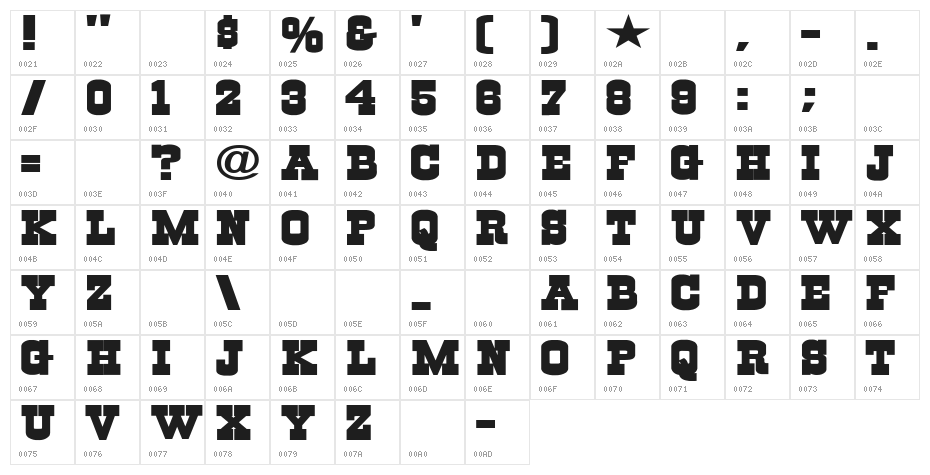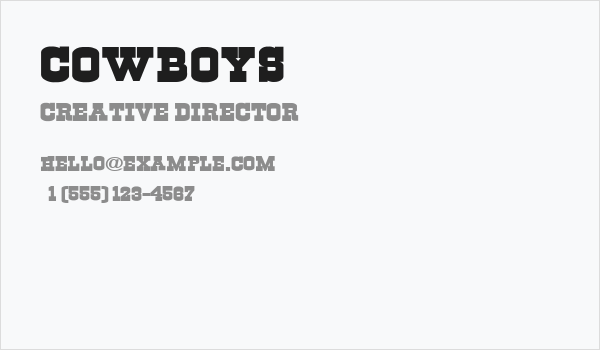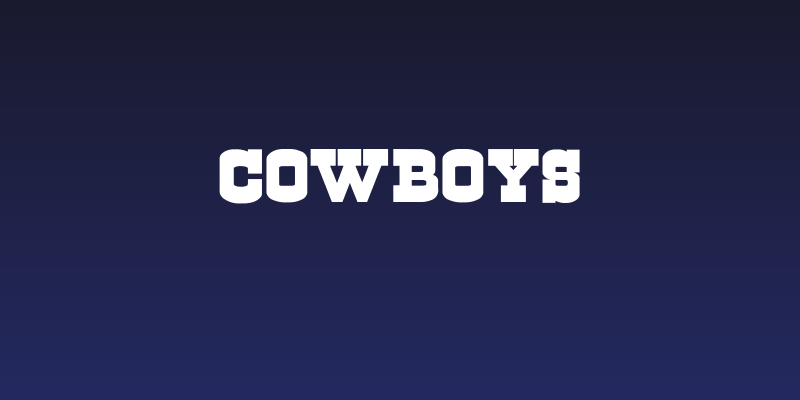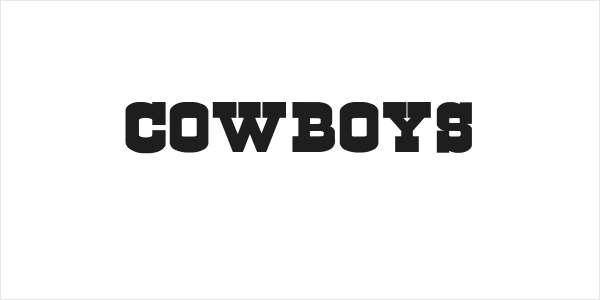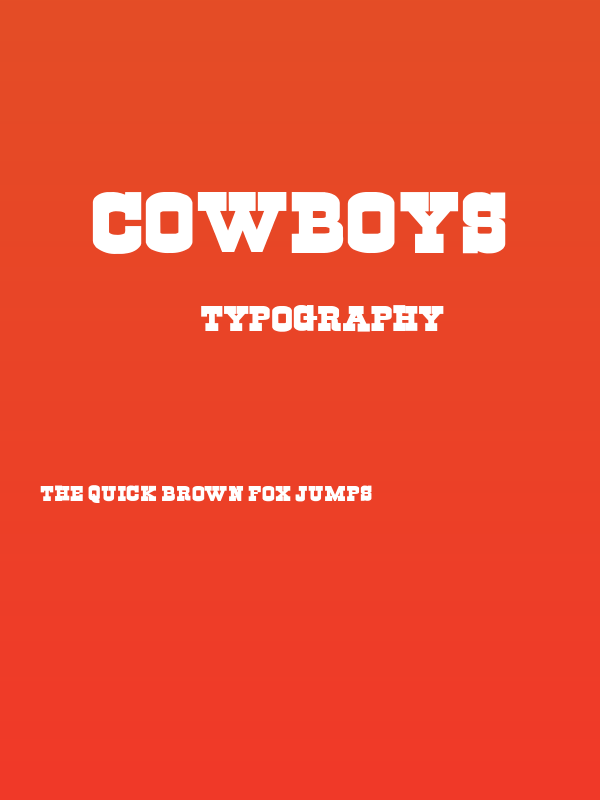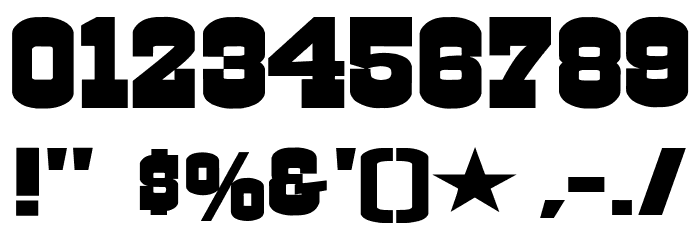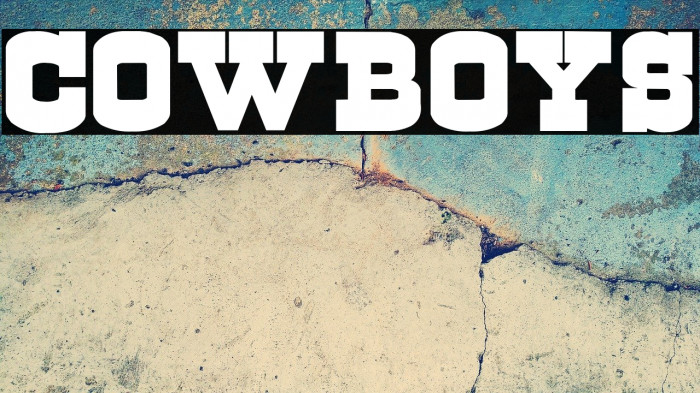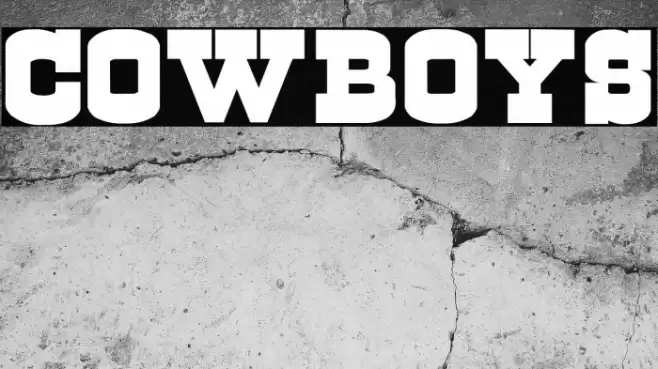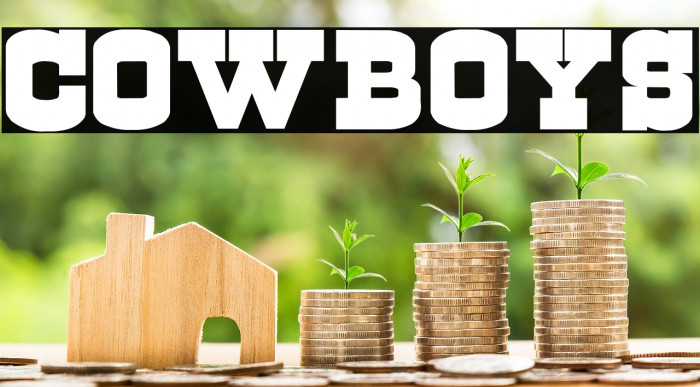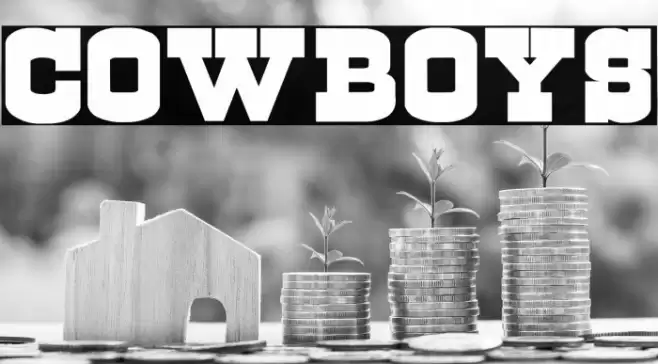
Cowboys Font
| النمط العام | Vintage |
| مشاريع مقترحة | Ideal for Western-themed posters, branding for rustic or vintage products, signage, and any design requiring a bold, attention-grabbing typeface. |